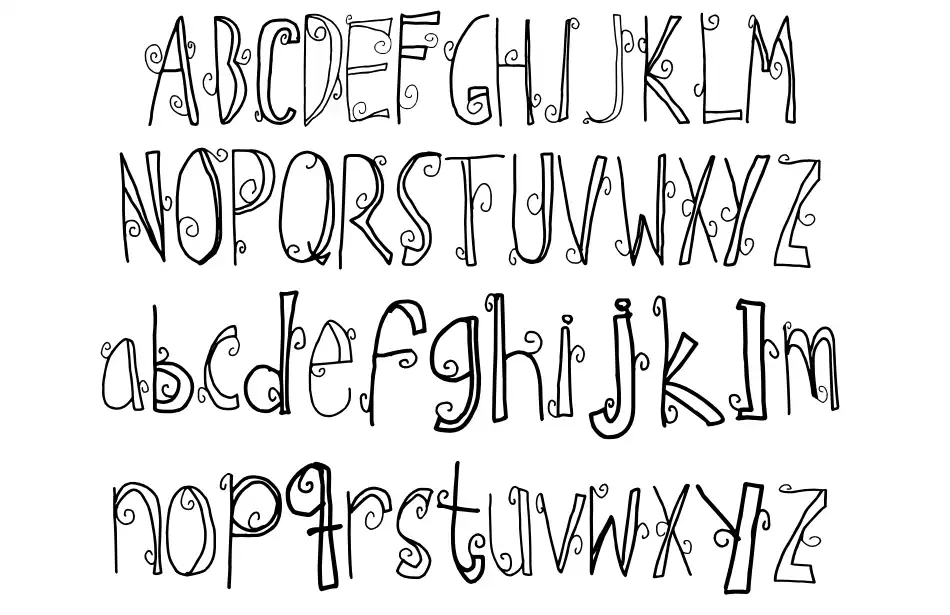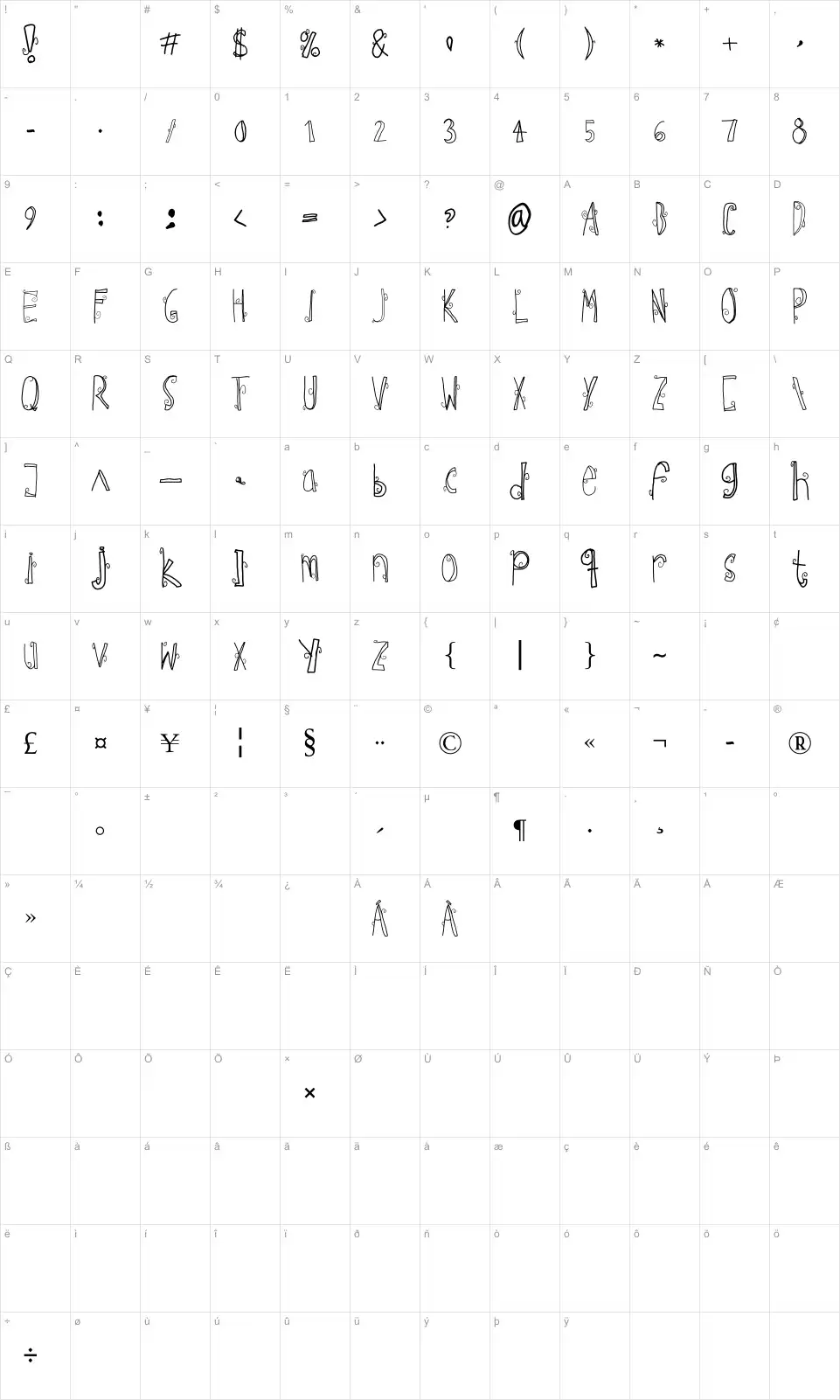
A Ebba Font é uma elegante fonte Fancy com uma curva delicada e curvilínea que combina uma sensação moderna com um toque romântico. Desenvolvida por Ebba, esta fonte curva é perfeita para adicionar um toque especial em sua próxima projeto gráfico. Se você está procurando por uma fonte de categoria Fancy, esta é uma ótima escolha. A Ebba Font está disponível em formato TTF, permitindo que você use e personalize conforme preferir. Com licença gratuita, você pode baixar o arquivo da fonte ou gerar um preview personalizado de texto online para ver como ela se destaca em seus projetos. Esta fonte foi adicionada em 12 de julho de 2022 e já foi baixada por 4419 pessoas, um número que testem prima sua popularidade. Com seu tamanho de apenas 38 KB, é compacta o suficiente para ser facilmente carregada em qualquer projeto.